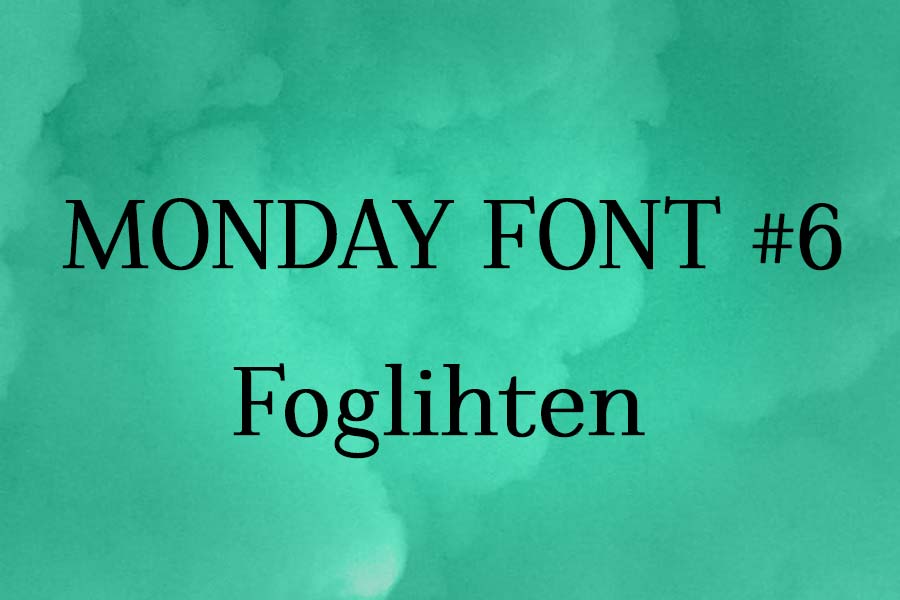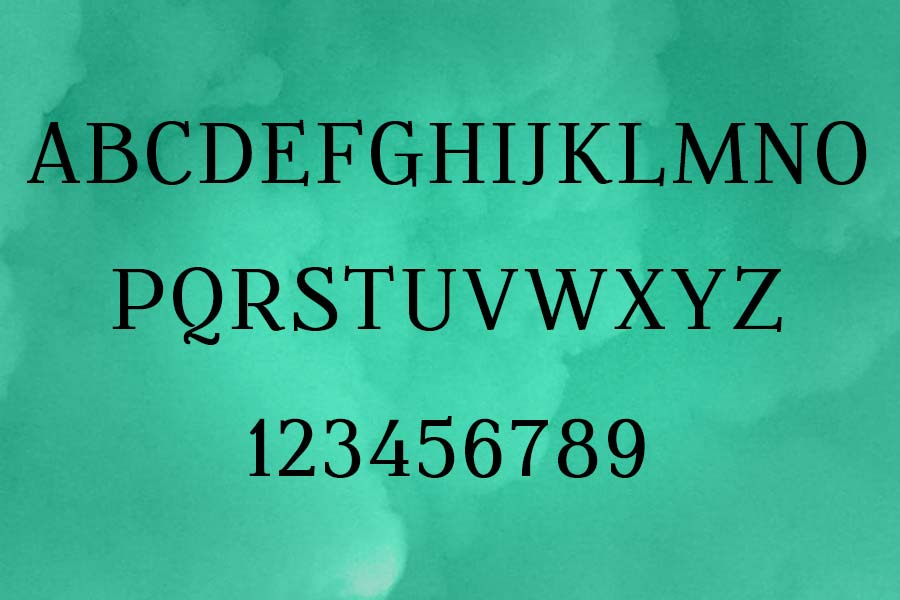
La tipografía elegida para el volumen #6 de Monday Font es Foglihten, una tipo con serifa elegante, bonita y con muchas posibilidades tanto en títulos como en párrafos.